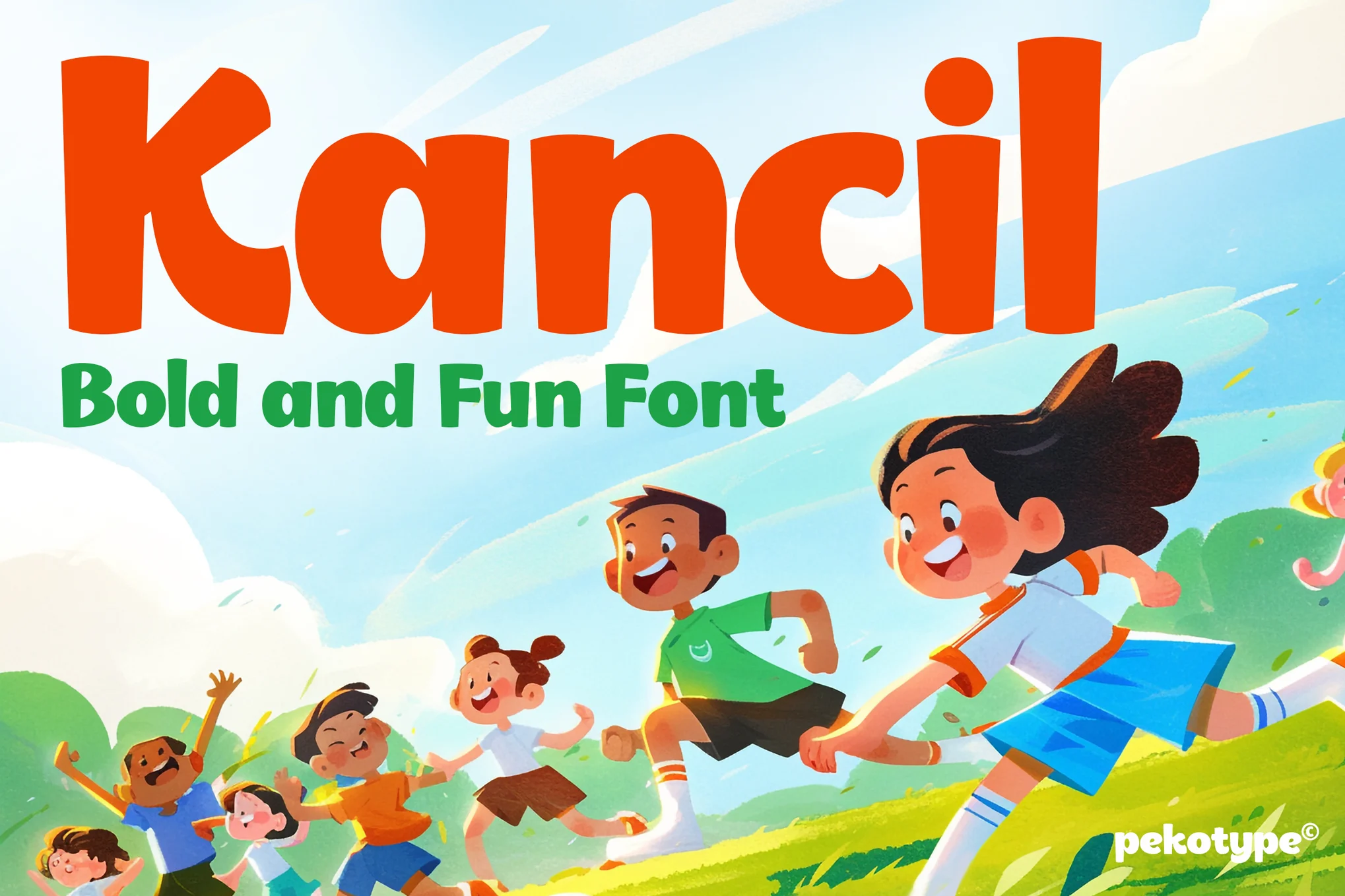
🎨 فونت KANCIL – بازیگوش، مدرن، پرانرژی!
KANCIL یک فونت نمایشی جذاب و بازیگوش است که با سبک sans-serif مدرن و انحناهای چشمنواز خود، طراوت و شخصیت را به طراحیهای شما میبخشد. اگر به دنبال فونتی هستید که در همان نگاه اول توجه مخاطب را جلب کند، KANCIL انتخابی بیرقیب است!
✨ ویژگیهای برجسته
- حروف بزرگ و کوچک با طراحی اختصاصی
- پشتیبانی از اعداد، علائم نگارشی و نمادها
- چندزبانه (Multilingual Support)
- وضوح بالا و خوانایی فوقالعاده
- مناسب برای تمام سنین و سبکهای طراحی
🎯 کاربردها
چه در حال طراحی لوگو باشید، چه بستهبندی محصولات، کتاب کودک، پوستر فیلم، پستهای شبکههای اجتماعی، رسانههای چاپی یا حتی بازیهای ویدیویی، KANCIL با شخصیت پرشور و انعطافپذیر خود، جلوهای خاص و متفاوت به پروژهتان میدهد.
💡 چرا KANCIL؟
این فونت تنها یک ابزار نیست، بلکه یک همراه خلاق برای ایدههای جسورانه و مفاهیم بازیگوشانه است. طراحی آن به گونهایست که میتواند هم برای پروژههای کودکانه و هم برندهای مدرن و خلاقانه مورد استفاده قرار گیرد.